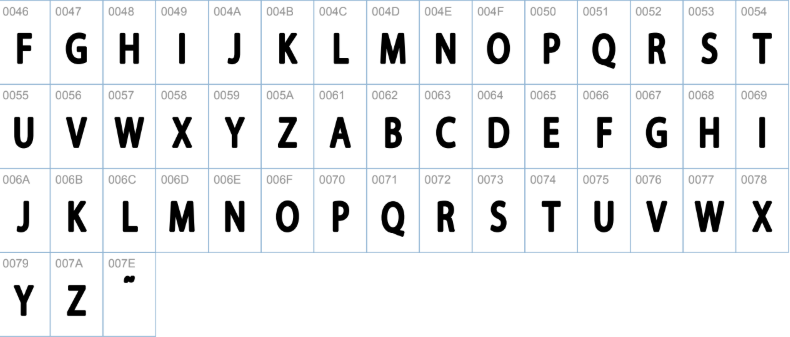
A temporada 2025/26 marcou o lançamento de um dos uniformes mais sofisticados da história recente do Sport Club do Recife. Em parceria com a Umbro, o “Leão da Ilha” apresentou seu terceiro uniforme (Third Kit), fugindo do tradicional rubro-negro para apostar em uma paleta elegante de azul petróleo com detalhes dourados.
Para designers gráficos, editores de PES/eFootball e criadores de conteúdo esportivo, ter a fonte correta é fundamental para manter a fidelidade visual do projeto. A tipografia utilizada nos nomes e números desta camisa complementa o design moderno, oferecendo uma leitura limpa e tecnológica que se destaca sobre a textura do tecido.
Estilo visual da tipografia
A tipografia do terceiro uniforme do Sport Recife segue a identidade global da Umbro para a temporada, mas com ajustes que valorizam a estética do clube pernambucano.
- Design e Traços: É uma fonte sans-serif (sem serifa) com peso robusto e cortes angulares estratégicos dentro dos números. Esses cortes conferem um aspecto industrial e veloz, moderno e agressivo, ideal para uniformes de performance.
- Aplicação no Kit: Na camisa Third (azul), a fonte é aplicada predominantemente na cor Dourada (Gold), criando um contraste luxuoso e de alta legibilidade.
- Identidade: Diferente das fontes retrô ou arredondadas de anos anteriores, esta tipografia transmite inovação e seriedade, alinhada com a proposta de um uniforme de gala para jogos noturnos e decisivos.